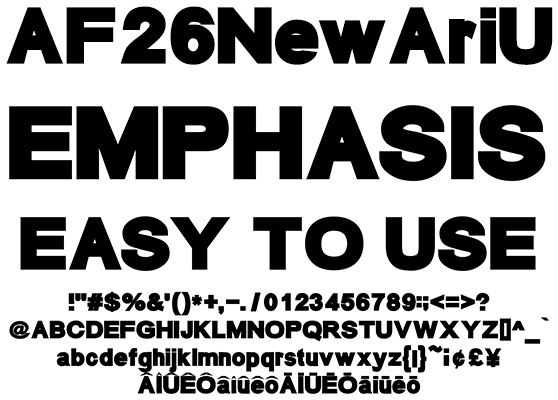
極太サンセリフ AF26NewAriU
AF26NewAriUZebra
極太で視認性を強調したサンセリフ欧文フォントです。インパクトを与えたいワードに適しています。平凡ながら極太デザインは違和感なくメッセージを浸透させます。記号類、マクロンやサーカムフレックスなどのダイアクリティカルマーク、訓令式やヘボン式で扱う Ô やŌを収録、人名地名でもお使い頂けます。